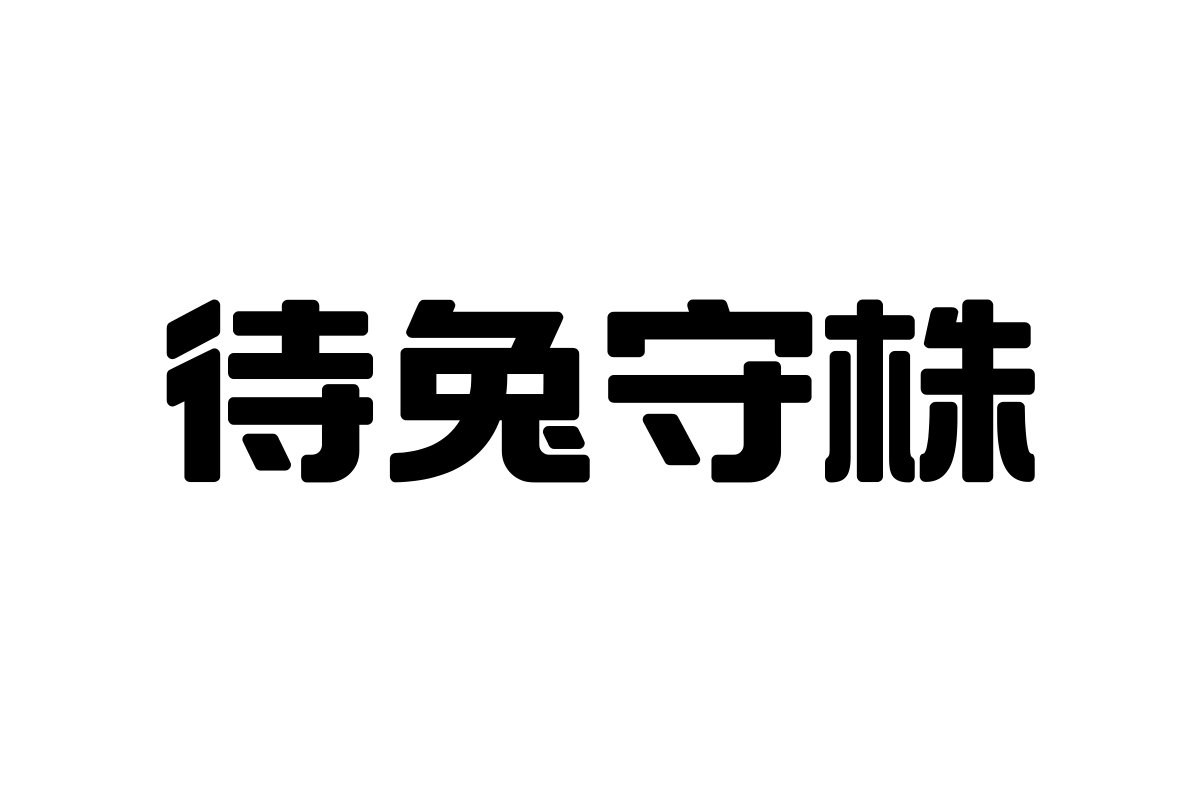
博瀚体是一款具有现代感和艺术气息的中文字体,它以简洁明快的风格,为设计作品带来独特的视觉冲击力。博瀚体采用了独特的笔触和结构,使得每个字符都充满了动感和生命力。它的笔画流畅自然,线条粗细适中,既适合用于标题、广告等需要突出显示的部分,也适合用于正文、说明文等需要清晰表达的部分。
博瀚体的设计灵感来源于自然界的元素,如山水、花鸟等,这些元素在字体中得到了巧妙的运用,使得整个字体既有艺术感又不失实用性。同时,博瀚体的字形设计也充分考虑了易读性,无论是大字还是小字,都能保持清晰的可识别度。
总的来说,博瀚体是一款非常适合现代设计的作品,它以其独特的风格和强大的表现力,赢得了广大设计师的喜爱和追捧。